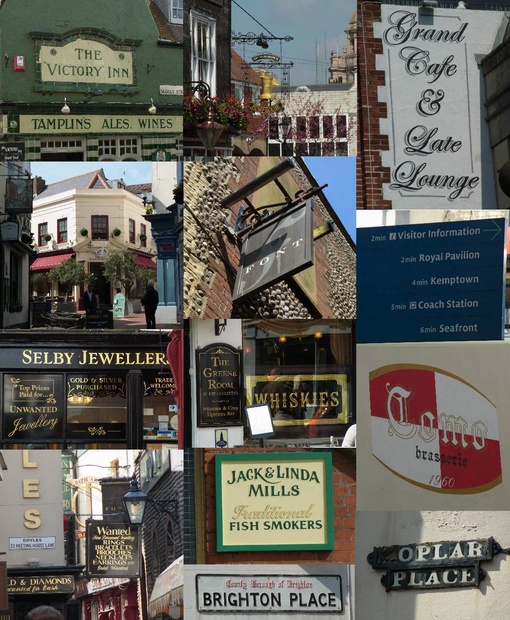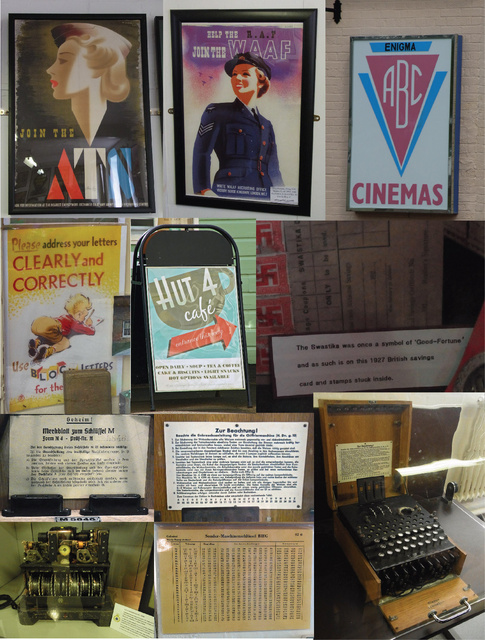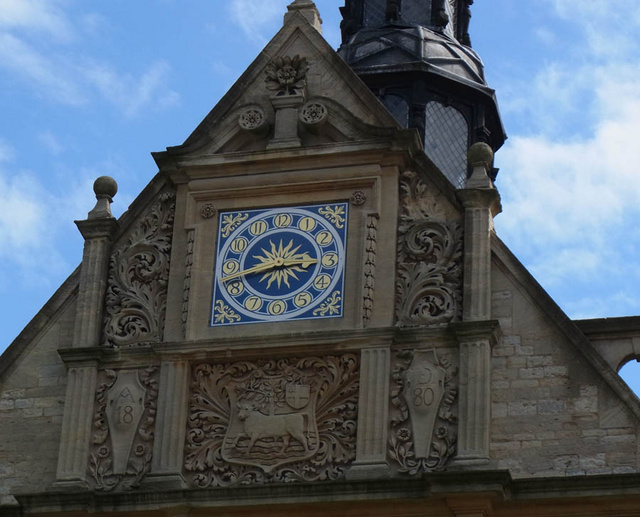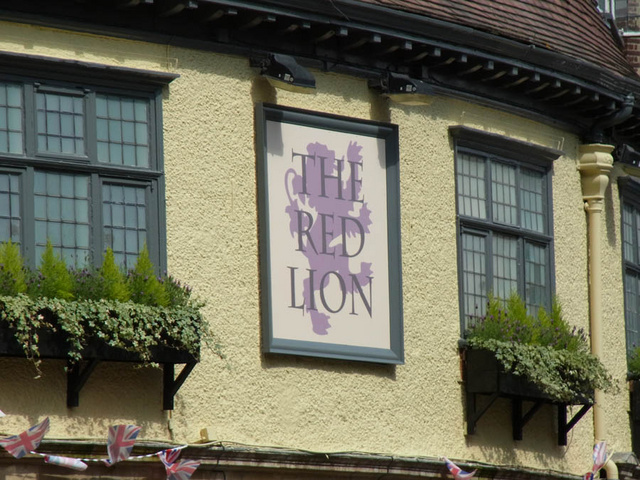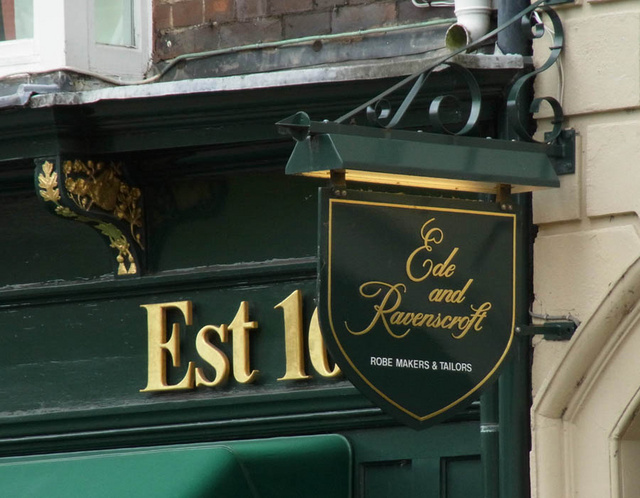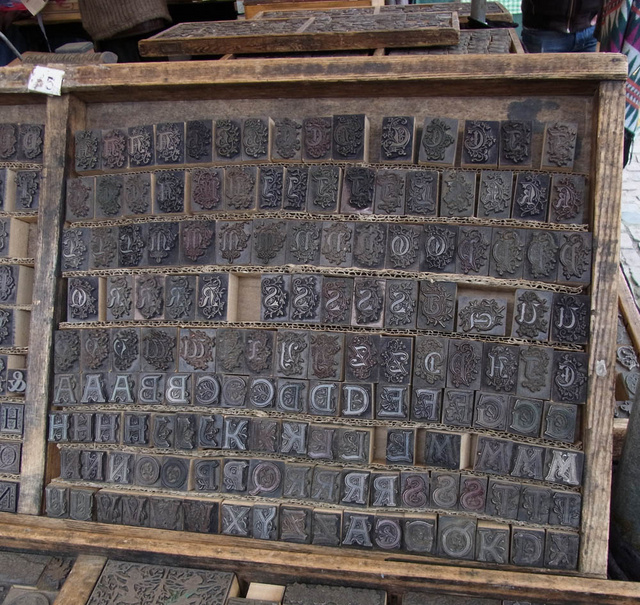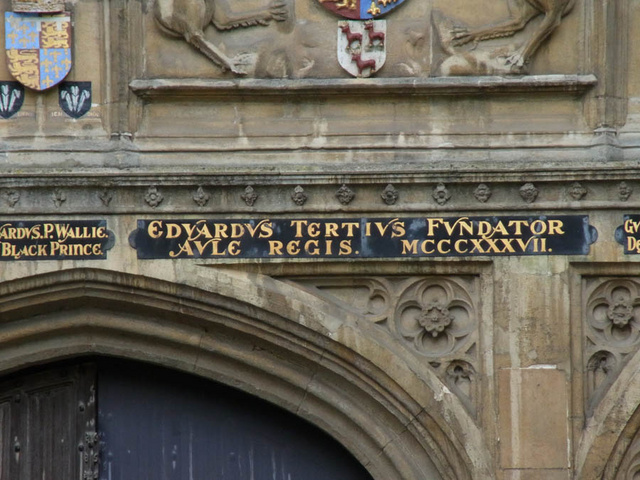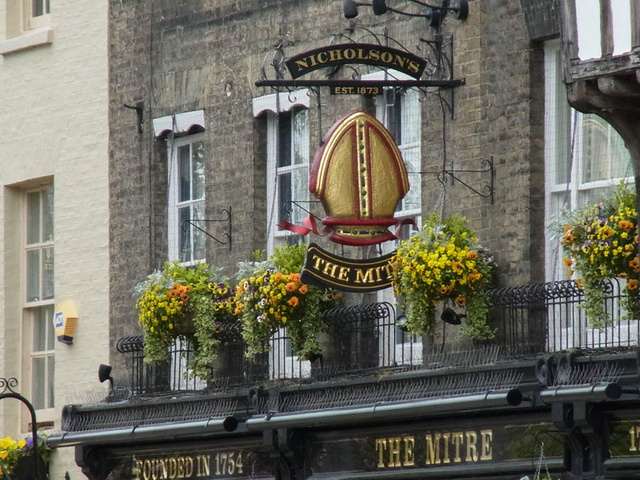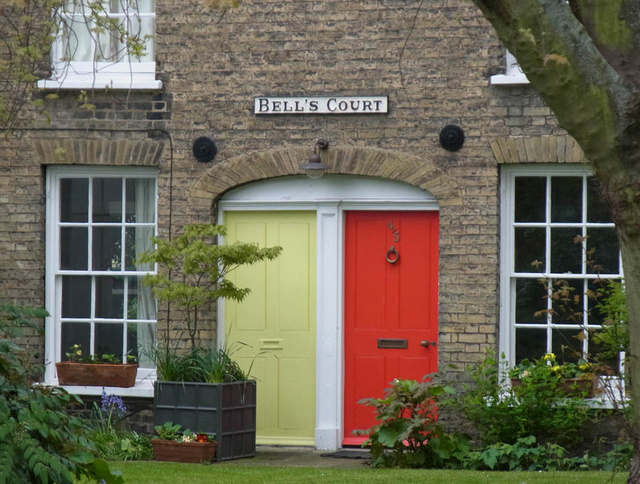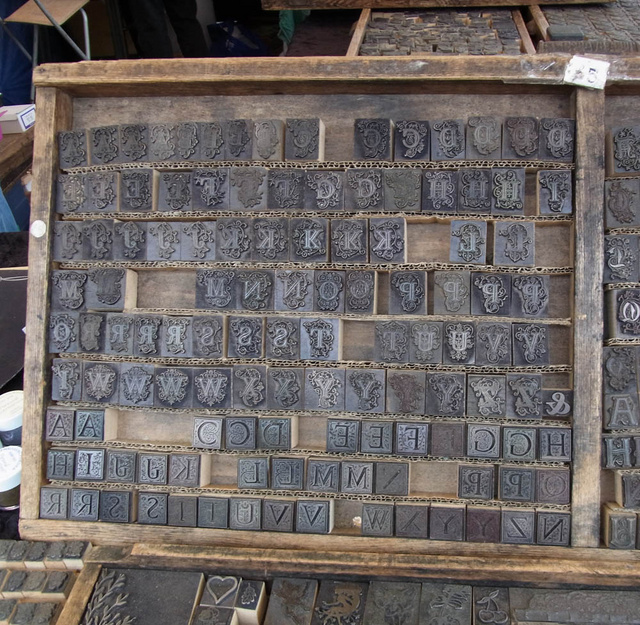
Typostreifzug durch die Stadt ...
Die würden in die Katzenschnurranstalt kommen :lol:
Schietwetterspaziergang durch meine Stadt …
ich zerbrech mir grad den kopf, wo pfeifen-tesch zu finden ist. den rest kenn ich ja, aber den kraken-rum hab ich noch nie gesehen
Colonnaden. ;-) Den Kraken-Rum finde ich auch bildhübsch. Wobei ich immer noch grübele, ob da Tintenfischtinte drin ist? Nächstes Mal frage ich …
Der Laden mit der Waschvolltomate fasziniert mich schon ewig. Er ist in der Osterstraße, Ecke Schulweg. Die Inhaber basteln seit Jahrzehnten sehr liebevoll ihre Werbung selber – und alles andere auch. Die Schaukästen vorm Laden sehen aus, als hätte ein Vorfahr sie zu Zeiten des Wirtschaftswunders gezimmert und in gelben Kreisen an den Fenstern wird in jedem Januar sorgfältig die Zahl ausgetauscht, die besagt, wie lange der Laden schon besteht. Dort gibt es Batterien für alles, Kuscheltiere, Lockenstäbe, Eierkocher, Nasenhaarschneider … Und außerdem stellen sie unseren Farbfernseher ein. Wenn wir einen haben. Ich liebe den Laden! :-P
Der Kraken-Rum gefällt mir. ...
Mir auch :-) Deren Website ist übrigens eine echte Schau, topmodern und doch sehr liebevoll weit ins letzte Jahrhundert gesetzt.
Er wird ja als "Black Spiced" angepriesen, vielleicht ist da Tintenfischtinte drin? Wer weiß …
Mir ist gerade aufgefallen, dass ich meine Urlaubsfotos gar nicht präsentiert habe :shock:
Also, dies war ein Tagesausflug nach Duderstadt (Nds.):
Ganz spannend ist die Mischung, die bei der alten Beschriftung mit neuer Werbung entsteht. Teilweise wurde da drauf eingegangen (auch wenn’s nicht immer gelungen ist) und manchmal wurde sich da völlig drüber hinweggesetzt ...
Und ein Suchspiel obendrein: Wo hat da jemand ein „F“ geklaut?
Man sieht den Kleber noch …
Flüchtige (typografische) Impressionen aus der (Englischen) Küstenstadt Brighton.
Und hier ein paar Impressionen (leider ohne Polfilter) aus Blechley Park (in der Nähe von Milton Keynes), eine »Dechiffrierungsfabrik« im 2. Weltkrieg in welcher die Nachrichten der Enigma- und Lorenz-Maschinen geknackt wurden (ist nur so halb stadtbezogen, paßt aber glaube ich trotzdem hierher …:roll:).
Selbstverständlich nicht von mir, aber vielleicht von Interesse: Ladenbeschilderungen von der Lower East Side Manhattans aus dem Jahr 1908, incl. jiddischer Beschriftung.
Falls jemand Interesse an zeitgenössischer Verwendung des Hebräischen Schriftsystems für Jiddisch haben sollte, sagt bitte Bescheid. Ich bin vor einer Weile mal durch Kiryas Joel im Bundestaat New York gefahren und habe bei der Gelegenheit die meisten dort sichtbaren Schilder fotografiert. Das Besondere an dem Ort: die Einwohner sind fast ausschließlich Jiddisch-Muttersprachler. Möglicherweise ist KJ sogar der größte primär jiddischsprachige Ort überhaupt. Das schlägt sich natürlich auch im Straßenbild wieder.